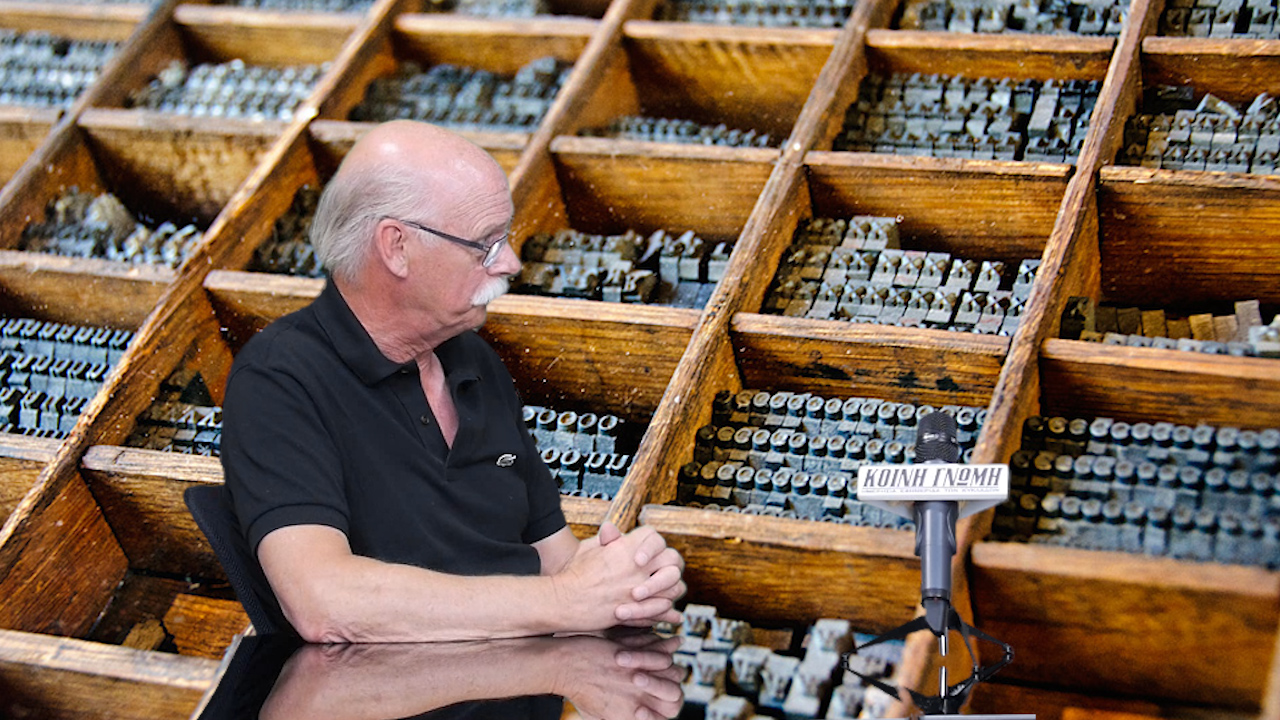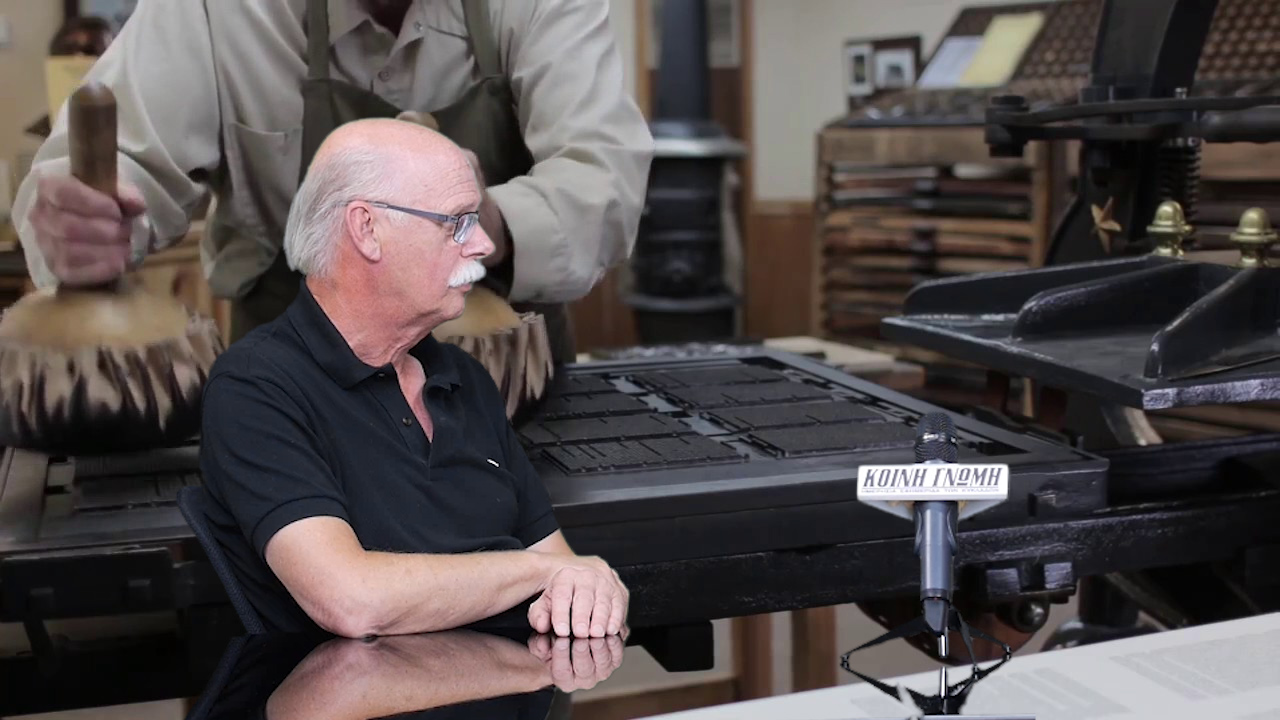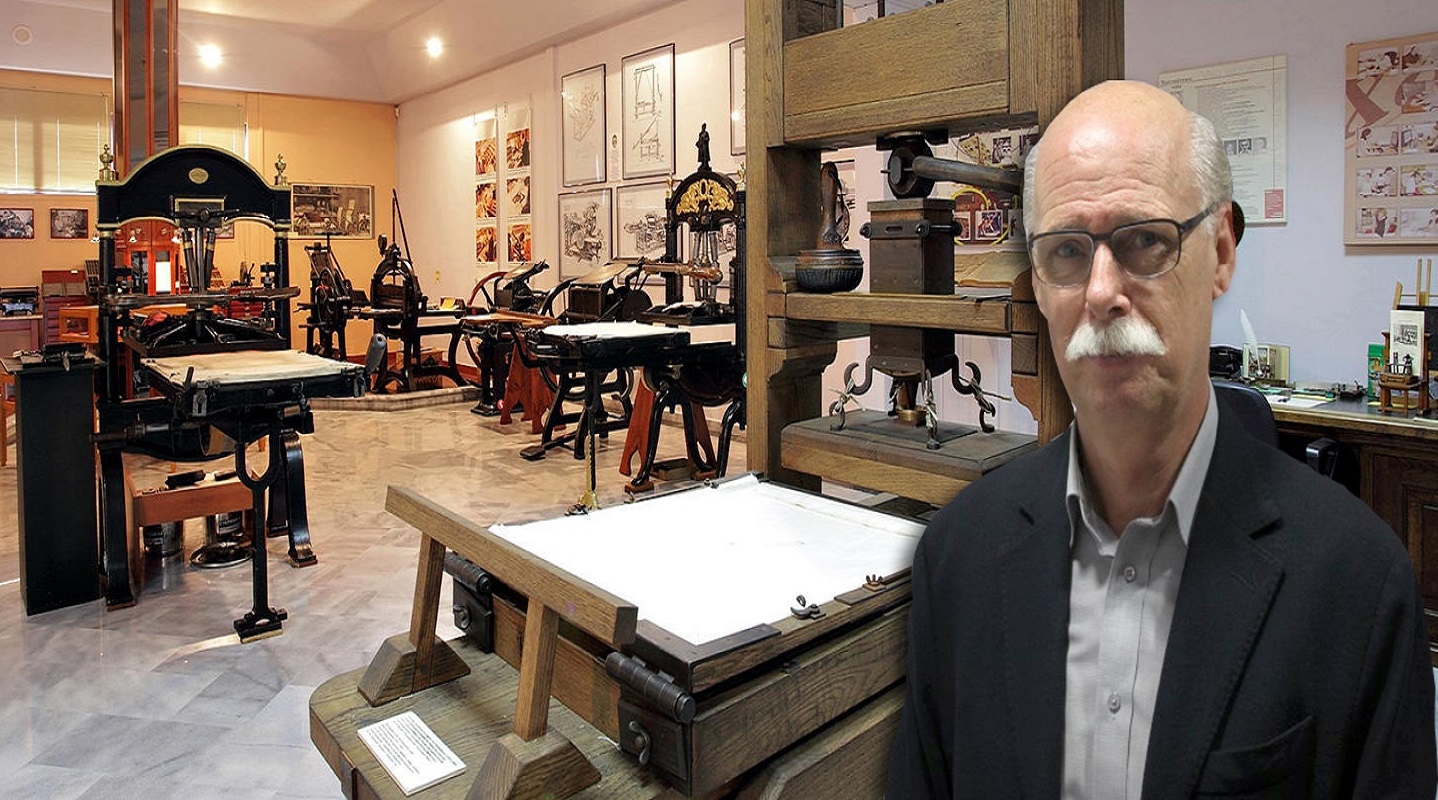
Ο πρόεδρος της Ένωσης Ευρωπαϊκών Μουσείων Τυπογραφίας, Δρ. Alan Marshall στην «Κοινή Γνώμη»
«Τα ψηφιακά μέσα έχουν ενισχύσει την τυπογραφία»
Στη Σύρο βρέθηκε ο πρόεδρος της Ένωσης Ευρωπαϊκών Μουσείων Τυπογραφίας, Γάλλος ιστορικός της βρετανικής προέλευσης, ειδικός στην ιστορία του βιβλίου και ιδιαίτερα την ιστορία της στοιχειοθεσίας, Δρ. Alan Marshall.
Η Ένωση Ευρωπαϊκών Μουσείων Τυπογραφίας πραγματοποίησε το ετήσιο συνέδριό της στα Χανιά της Κρήτης και στο νέο Μουσείο Τυπογραφίας Χανίων, όπου παραβρέθηκε και ο Δρ. Marshall. Στο πλαίσιο της επίσκεψής του στην Ελλάδα, επόμενος σταθμός υπήρξε το νησί της Σύρου, στη διάρκεια του οποίου ο πρόεδρος της ΕΕΜΤ, επισκέφτηκε και ξεναγήθηκε στην εκτυπωτική μονάδα της Τυποκυκλαδικής Α.Ε., απ’ όπου αποκόμισε εξαιρετικά θετικές εντυπώσεις, τόσο για τη δράση της εντός Ελλάδος, όσο και για τις προοπτικές που ανοίγονται για την επιχείρηση και στο εξωτερικό.
Παράλληλα, ο Δρ. Marshall μίλησε στην Κοινή Γνώμη, για τα μουσεία τυπογραφίας σε Ελλάδα και Ευρώπη, την ποιότητα, των παραδοσιακών, αλλά και τωννέων τεχνικών, ενώ κατέθεσε και την άποψή του, σχετικά με το μέλλον της τυπογραφίας, στην ψηφιακή εποχή.
Κύριε Marshall, βρεθήκατε στο ετήσιο συνέδριο της ΕΕΜΤ στα Χανιά. Ποιες οι εντυπώσεις σας από το Μουσείο Τυπογραφίας Χανίων;
Dr. Alan Marshall: Το ετήσιο συνέδριο της Ένωσης Ευρωπαϊκών Μουσείων Τυπογραφίας πραγματοποιήθηκε φέτος στα Χανιά. Πριν περίπου δύο χρόνια, ένας φίλος μου από το Μουσείο Τυπογραφίας Χανίων προσφέρθηκε να φιλοξενήσει τη διοργάνωση και ενθουσιαστήκαμε, τόσο λόγω του Μουσείου, όσο και λόγω της ευκαιρίας που μας δόθηκε να έρθουμε στην Ελλάδα και να εντρυφήσουμε σε έναν διαφορετικό τυπογραφικό πολιτισμό και ιστορία. Έχει διαφορές η εγχώρια ιστορία της τυπογραφίας στην Ελλάδα. Η τυπογραφία ήρθε στη χώρα αρκετά αργότερα από την υπόλοιπη Ευρώπη και η ιστορία της είναι σχετικά πρόσφατη. Συνεπώς η ιστορία της είναι κάπως διαφορετική, από άλλες χώρες που η τυπογραφία έχει τις ρίζες της στα τέλη του 15ου αιώνα.
Στα Χανιά υπάρχει ένα πολύ όμορφο μουσείο και πολύ ενδιαφέρον. Έχει μία μεγάλη και ευρεία συλλογή από εξοπλισμό, τυπογραφικά ντοκουμέντα, όπως επίσης και καταγραφή των δεξιοτήτων και των γνώσεων, που απαιτείται για τη χρήση των μηχανημάτων.
Το Μουσείο Τυπογραφίας Χανίων έχει επίσης πολύ ενδιαφέρουσες πρωτότυπες συλλογές, αλλά και σημαντικές δραστηριότητες. Τέτοιες συλλογές και δραστηριότητες μπορεί να βρει κανείς σε μουσεία σε όλη την Ευρώπη. Μεγάλο ενδιαφέρον παρουσιάζουν και οι “ρίζες” του μουσείου, καθώς διαθέτει μία μακρά παράδοση, περίπου 2 αιώνων, στην τυπογραφία, με οικογένειες τυπογράφων που επί 2 αιώνες παραμένουν προσηλωμένοι και ενδιαφέρονται για την τέχνη αυτή. Και το μουσείο αναδεικνύει ακριβώς αυτό. Οι άνθρωποι που εμπλέκονται με το μουσείο, ασχολούνται με την τυπογραφία και την έκδοση εντύπων, έχουν επενδύσει χρόνο, προσπάθεια και αφοσίωση να συγκεντρώσουν το υλικό, τα μηχανήματα, τα έγγραφα, τα βιβλία, προκειμένου να δημιουργήσουν ένα μουσείο, που πραγματικά αξίζει να το επισκεφτεί κανείς.
Ποιος είναι ο ρόλος ενός μουσείου τυπογραφίας; Είναι η διατήρηση και η ανάδειξη της τυπογραφικής ιστορικής κληρονομιάς, η εκπαίδευση και ενημέρωση των νεότερων, ή ακόμη και η διαπαιδαγώγηση των σημερινών τυπογράφων;
Dr. Alan Marshall: Είναι δύσκολο να μιλήσει κανείς για τα μουσεία τυπογραφίας ως σύνολο, καθώς υπάρχουν σχεδόν τόσα είδη μουσείων τυπογραφίας, όσο περίπου και τα είδη της τυπογραφίας. Υπάρχουν μουσεία τυπογραφίας με διαφορετικά είδη συλλογών, μηχανημάτων και εξαρτημάτων, ντοκουμέντων, εργαστηρίων και εκπαιδευτικών δραστηριοτήτων και κάθε μουσείο, ανάλογα με την περίπτωση, την προέλευσή του, τον προϋπολογισμό του – αναπόφευκτα – έχει ένα διαφορετικό μείγμα όλων αυτών των παραγόντων.
Υπάρχουν όμως και κοινοί παράγοντες στα μουσεία τυπογραφίας. Η τυπογραφία εισήχθη από τον Γουτεμβέργιο και έχει ιστορία πάνω από 500 χρόνια. Είναι επίσης άρρηκτα συνδεδεμένη, με όλες της μορφές της πνευματικής, πολιτιστικής προόδου του ανθρώπου. Δεν μπορεί να μιλά κανείς για τον Δυτικό πολιτισμό, χωρίς να αναφερθεί και στην τυπογραφία. Ιστορικά, λοιπόν, είναι εξαιρετικά σημαντική.
Είναι επίσης πολύ σημαντική, καθώς αποτελεί τη «μητέρα» των Μέσων Μαζικής Ενημέρωσης, όπως τα ξέρουμε σήμερα. Τα σύγχρονα ΜΜΜ δεν έπεσαν από κάποιο δέντρο, ή από κάποιο υπολογιστή, ή από κάποια τηλεόραση. Προέρχονται από κάπου και το κύριο σημείο αναφοράς, είναι η τυπογραφία, το έντυπο, ως το πρώτο μέσο μαζικής ενημέρωσης, το πρώτο μέσο επικοινωνίας πληροφοριών, σε μεγάλη κλίμακα.
Τα μουσεία τυπογραφίας δίνουν τη δυνατότητα να δει κανείς, από πού ξεκίνησε και από πού προέρχεται η σημερινή μορφή επικοινωνίας των πληροφοριών.
Με αφορμή την τεράστια σημασία της τυπογραφίας στην ιστορία, που προαναφέρατε, τα τελευταία χρόνια, φαίνεται τα ψηφιακά μέσα και το ίντερνετ να έχουν παραγκωνίσει τα έντυπα μέσα. Ως επιστήμων, που έχει μελετήσει την πορεία της τυπογραφίας μέσα στους αιώνες, θεωρείται πως ενδεχομένως ερχόμαστε σταδιακά αντιμέτωποι με το τέλος της τυπογραφίας;
A.M.: Θα πρέπει να διευκρινίσουμε, ότι υπάρχουν δύο έννοιες της τυπογραφίας. Η τυπογραφία, με την έννοια του εντύπου, της εκτύπωσης μελανιού σε χαρτί και η πιο γενική έννοια της τυπογραφίας, που αφορά στην χρήση συνόλων γραμμάτων προκειμένου να οργανώσει κανείς ιδέες σε κείμενο, με τη βοήθεια ίσως εικόνων, σε μία δισδιάστατη επιφάνεια, που παραδοσιακά μπορεί να είναι το χαρτί, αλλά στο σήμερα, μπορεί να είναι και μία οθόνη.
Η δεύτερη έννοια της τυπογραφίας, κατά την άποψή μου, δεν μπορεί να εξαφανιστεί, εκτός αν στο μέλλον γυρίσουμε σε ένα καθαρά προφορικό πολιτισμό.
Είναι περίπλοκο, καθώς υπάρχουν τομείς των ψηφιακών μέσων, που έχουν όντως παραγκωνίσει τα έντυπα μέσα, αλλά υπάρχουν άλλοι τομείς, σημαντικοί τομείς, όπου τα ψηφιακά μέσα έχουν ενισχύσει την τυπογραφία, κατά κάποιο τρόπο. Υπάρχουν οι ηλεκτρονικές εκδόσεις, μέσω των οποίων, όλοι μας, μπορούμε να είμαστε τυπογράφοι, σήμερα, με τους υπολογιστές μας, ενώ εκτυπώνουμε μελάνι σε χαρτί, κάποιες σελίδες, συνήθως, για ίδια χρήση, ή για να δώσουμε σε κάποιον να το χρησιμοποιήσει, όπως σε ένα γραφείο. Πολύ συχνά, αυτού του τύπου τα έγγραφα διακινούνται σε μεγάλο βαθμό.
Αυτό που έχουμε δει τα τελευταία 50-100 τελευταία χρόνια, είναι μία διεύρυνση των ορίων και των δυνατοτήτων της τυπογραφίας κειμένου σε χαρτί. Ποτέ πριν δεν εκτυπώναμε τόσο πολύ, όσο εκτυπώνουμε τώρα. Είναι πολύ διαφορετικός ο τρόπος, είναι μία γκρίζα ζώνη. Η τυπογραφία παραδοσιακά ήταν μία τέχνη των τυπογράφων μόνο. Προϋπέθετε μία τεχνογνωσία και ήταν θέμα εξοπλισμού, ο οποίος ήταν κοστοβόρος, απαιτούσε μακρά εξάσκηση. Πλέον δεν γίνεται έτσι. Ο καθένας σήμερα μπορεί να φτιάξει το δικό του έντυπο. Ως εκ τούτου, η πρόοδος της τεχνολογίας διεύρυνε τα σύνορα στον τομέα.
Ποια είναι η άποψή σας, για τις σύγχρονες μεθόδους τυπογραφίας, σε σχέση με τις παραδοσιακές, σε επίπεδο ποιότητας;
A.M.: Υποψιάζομαι ότι η αναλογία της ποιότητας δεν έχει αλλάξει σχεδόν καθόλου. Η σύγχρονη γραφιστική παραγωγή είναι εκπληκτική. Είναι εφευρετική, συνεχώς ανανεώνεται. Πολλοί άνθρωποι τη θεωρούν ψυχρή, σε σχέση με το παλαιού τύπου έντυπο, όπου μπορούσες να νιώσεις το αποτύπωμα του μετάλλου στο χαρτί, σε αντίθεση με την εκτύπωση σε γυαλιστερό χαρτί κλπ. Αυτά τα πράγματα αλλάζουν, η ιστορία τους είναι κυκλική. Παρ’ όλα αυτά, σήμερα γίνεται μία πολύ υψηλής ποιότητας δουλειά και ευρύτερη απ’ ότι στο παρελθόν.
Υπάρχει πάντα μία τάση να θεωρούμε ότι οι παραδοσιακοί τυπογράφοι, είναι οι θεματοφύλακες της τυπογραφικής ποιότητας. Αξίζει να υπενθυμίσουμε, ότι πάντοτε υπήρχαν τυπογράφοι, οι οποίοι ενδιαφέρονταν περισσότερο να βγάλουν χρήματα, από το να κάνουν μία καλή δουλειά. Το 15ο αιώνα, τον 16ο, 18ο, υπήρχαν πολύ κακοί τυπογράφοι, που έκαναν πολύ κακή δουλειά. Μπορεί να βρει κανείς και πολύ καλούς τυπογράφους.
Στην πραγματικότητα δεν ήταν ποτέ θέμα εξοπλισμού, διότι ένας κακός τυπογράφος, με πολύ καλό εξοπλισμό, μπορεί να κάνει μία πολύ κακή δουλειά, ενώ ένας καλός τυπογράφος, με φτωχό εξοπλισμό, μπορεί ακόμη να κάνει μία πολύ καλή δουλειά. Είναι θέμα γνώσης, αφοσίωσης, επικοινωνιακών χαρισμάτων, ικανοτήτων, αλλά και να έχει κανείς ταλέντο, να έχει ικανότητα να αναγνωρίζει τι είναι αισθητικά ευχάριστο.
Δεν υπάρχουν συγκεκριμένοι κανόνες για να είναι κανείς καλός τυπογράφος. Υπήρχε, υπάρχει και θα υπάρχει πάντοτε μία ιεραρχία από τους καλύτερους των καλύτερων, έως τους χειρότερους των χειρότερων. Έτσι είναι σήμερα και έτσι ήταν και στο παρελθόν.